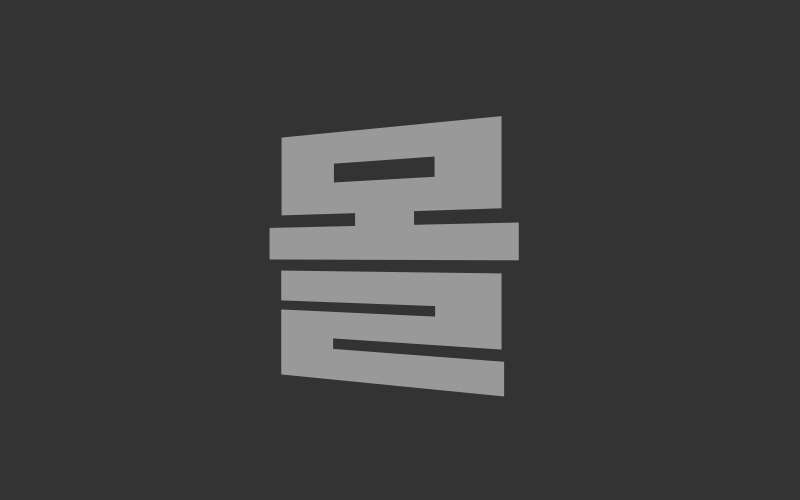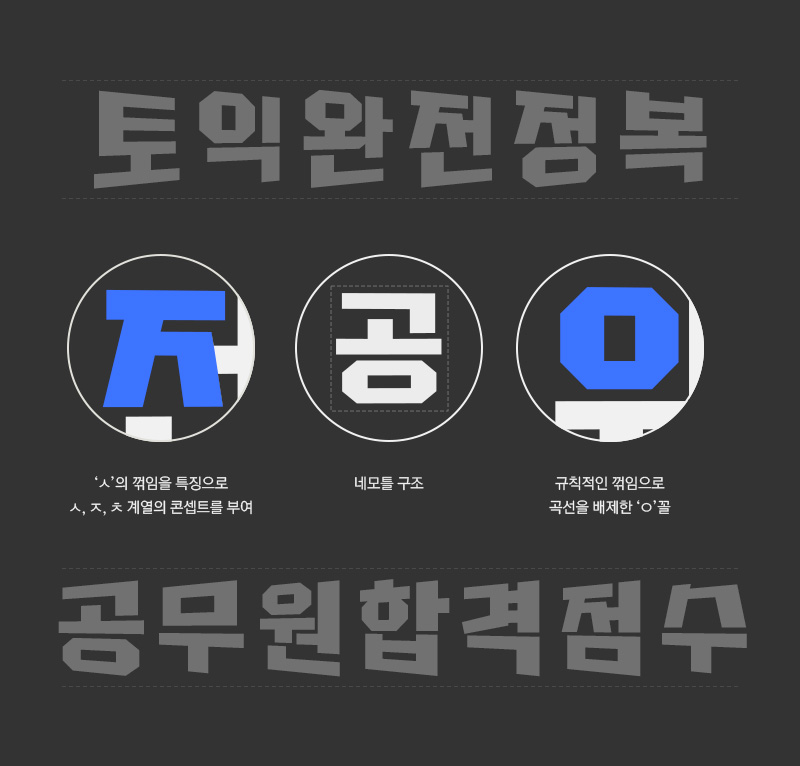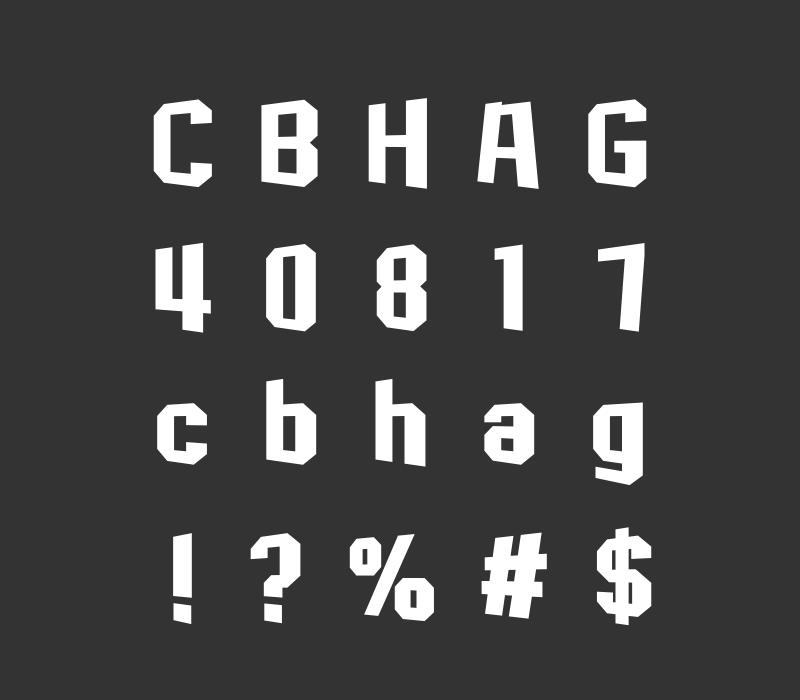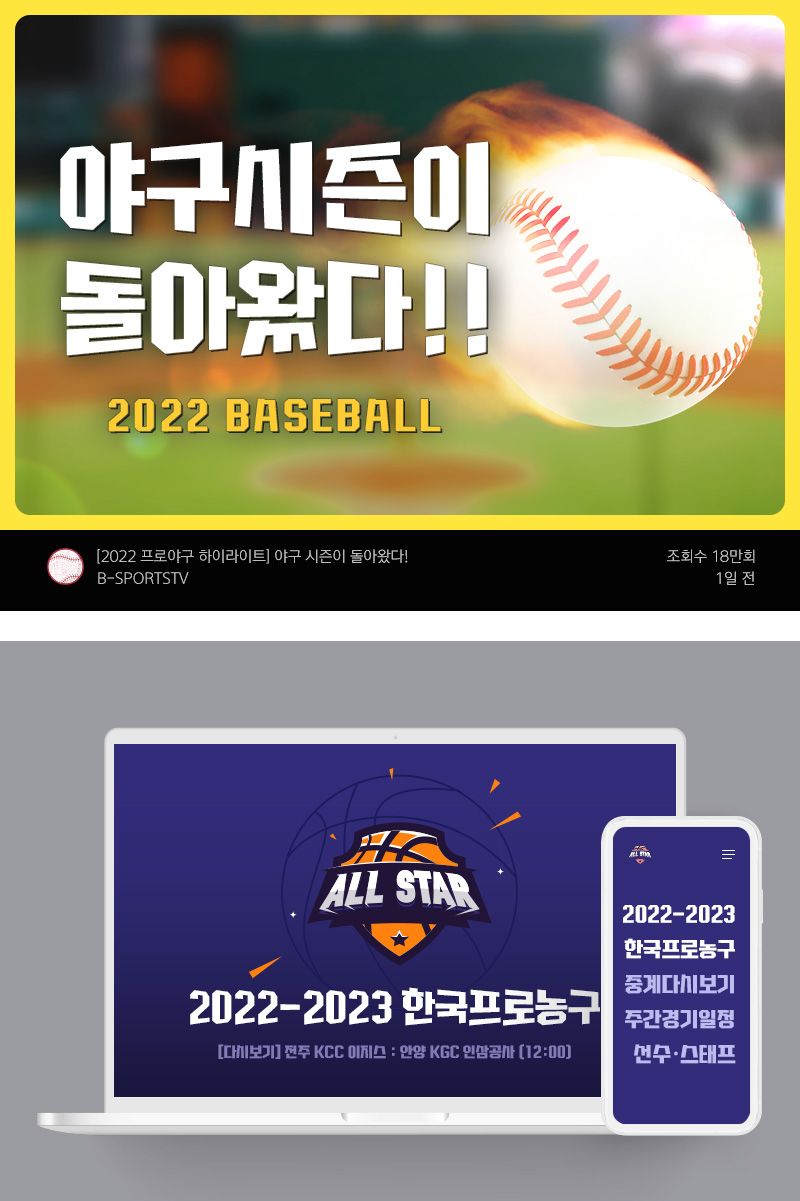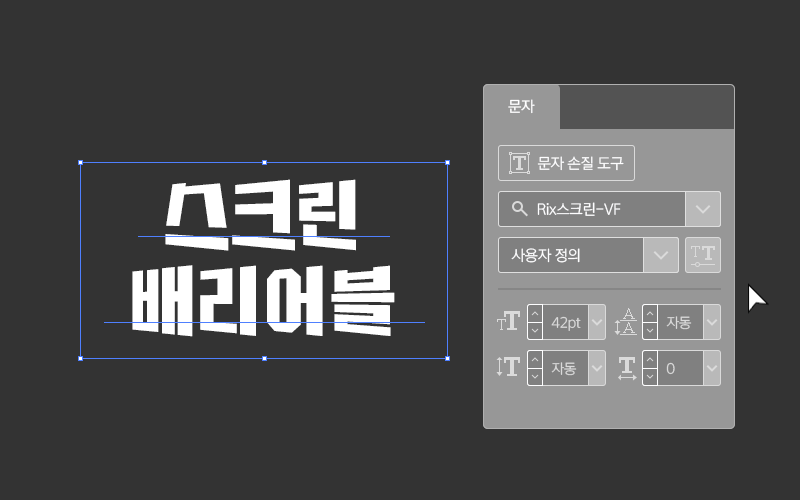
RixScreen-VF
외곽라인 획의 꺾임이 독특한 Rix영웅 서체를 기반으로 제작한 배리어블 폰트입니다.
글자마다 중심 축을 기준으로 좌우로 기울어져 입체적인 원근감을 느낄 수 있습니다.
두껍고 단단한 획의 움직임이 재미있고 역동적인 서체로 광고 등의 타이틀에 쓰기 좋습니다.
배리어블 폰트란, 사용자가 직접 글자의 속성을 조정할 수 있는 서체입니다.
좌우로 기울기를 주어 역동감이 느껴지는 한글 모듈을 사용합니다.
영문, 약물의 디자인은 한글과 동일한 특징을 가지고 있어 혼용 시 조화롭습니다.